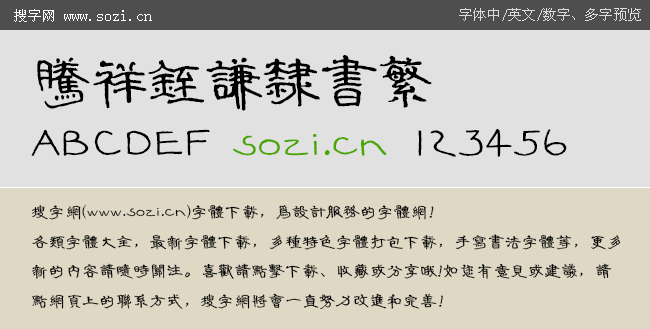
騰祥铚謙隸書繁
搜字網(wǎng)提供一款騰祥铚謙隸書繁中文藝術(shù)字體下載,騰祥铚謙隸書繁字體是一款手寫風(fēng)格的隸書字體,字體樸素?zé)o華,飽含古時之風(fēng)韻。 可用于出版印刷、廣告設(shè)計 網(wǎng)頁設(shè)計、包裝設(shè)計、屏幕顯示等領(lǐng)域。